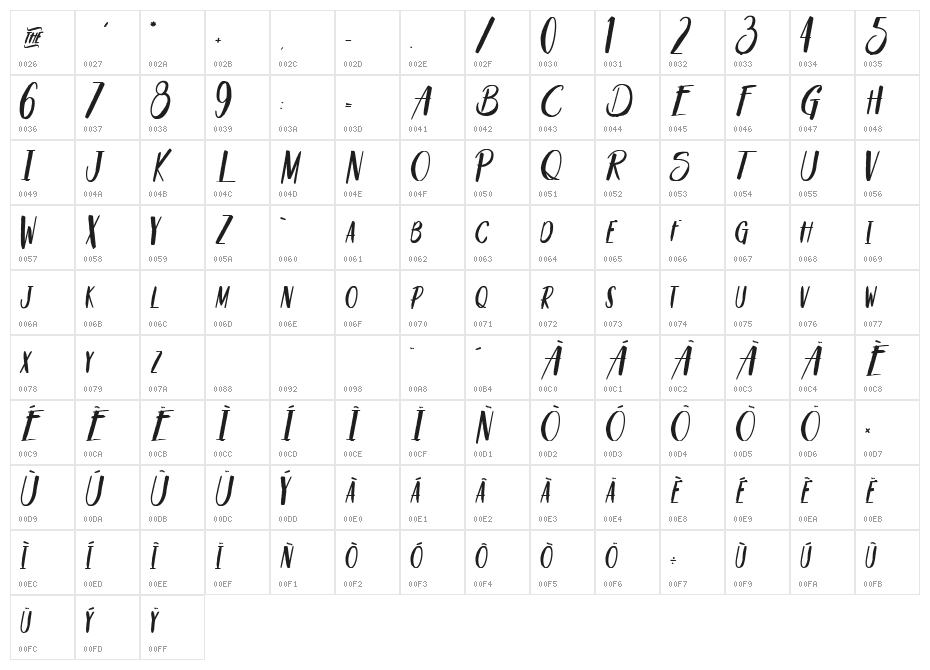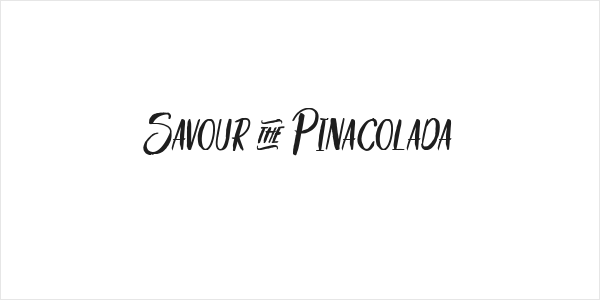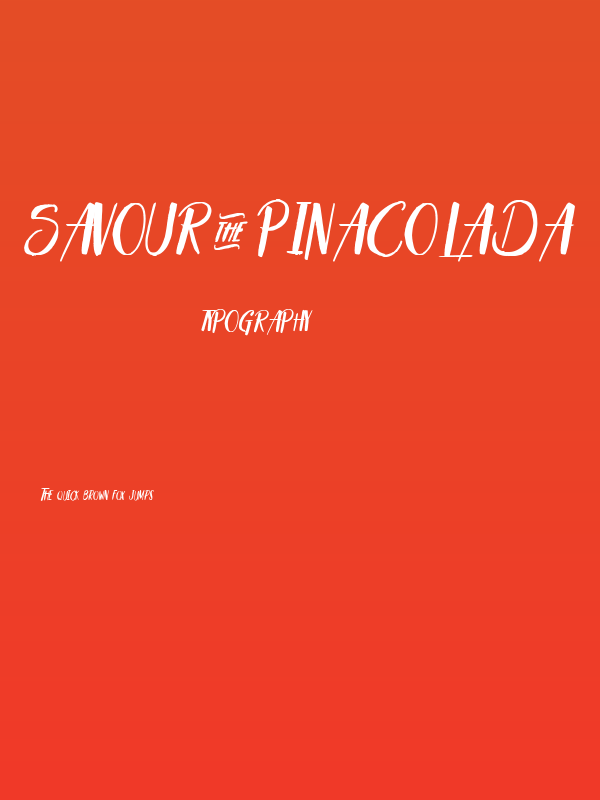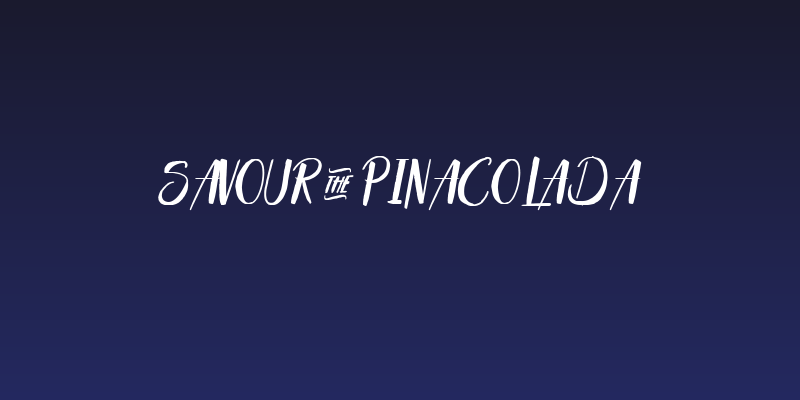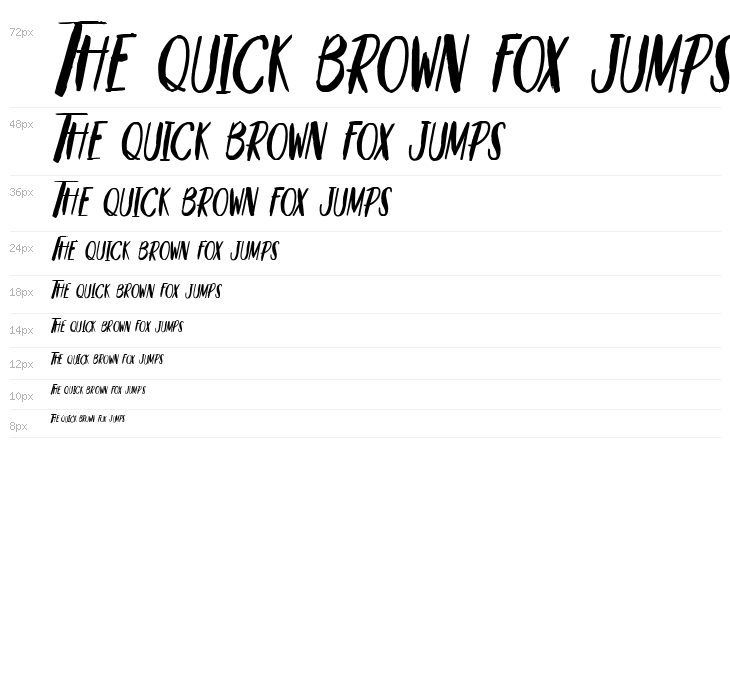
Savour&Pinacolada Font
| Anwendungsfall | Logos, Headlines, Posters |
| Vorgeschlagene Projekte | Ideal for branding, packaging design, posters, and social media graphics where a creative and energetic touch is desired. |
Savour&Pinacolada